いざというときに!「ビャンビャン麺」に対応している日本語フリーフォント
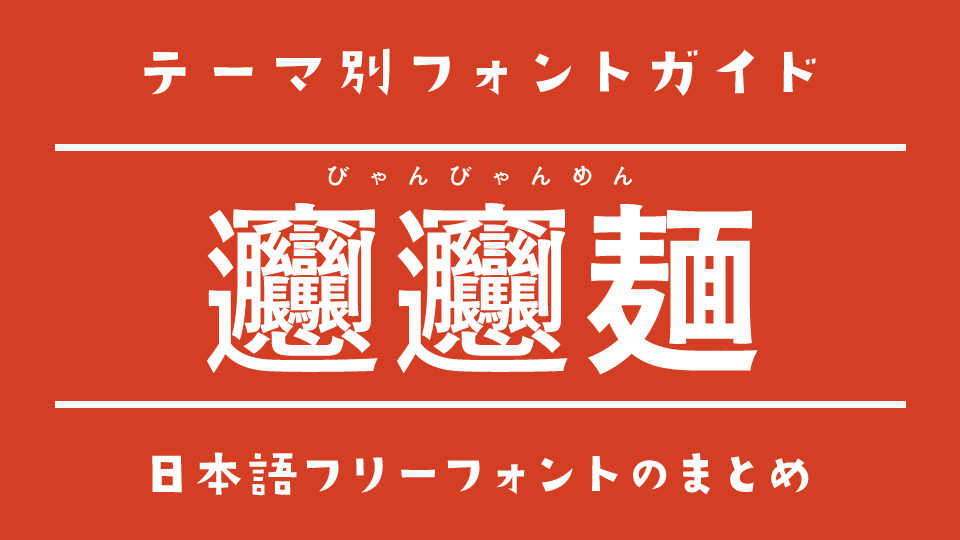
今回は、いざというときに役立つ「ビャンビャン麺」の文字を表示できる日本語フリーフォントをご紹介します。
「ビャンビャン麺」は、画数が非常に多く、一般的な日本語フォントでは表示できないこともある珍しい漢字です。入力したはずなのに四角い記号になったり、別のフォントへ自動的に置き換わったりして、デザイン制作で困った経験がある方もいるのではないでしょうか。
今回は、「ビャンビャン麺」という難しい表記に対応し、文字の形を正しく表示できるフリーフォントを厳選しました。中華料理店のメニューや旅行記事、難読漢字を扱うコンテンツ、フォントの収録文字を試したいときなど、いつか訪れるかもしれないを入力する日”に備えて、ぜひ参考にしてみてください。
「びゃん」が表示できる!びゃんびゃん麺対応の日本語フリーフォント
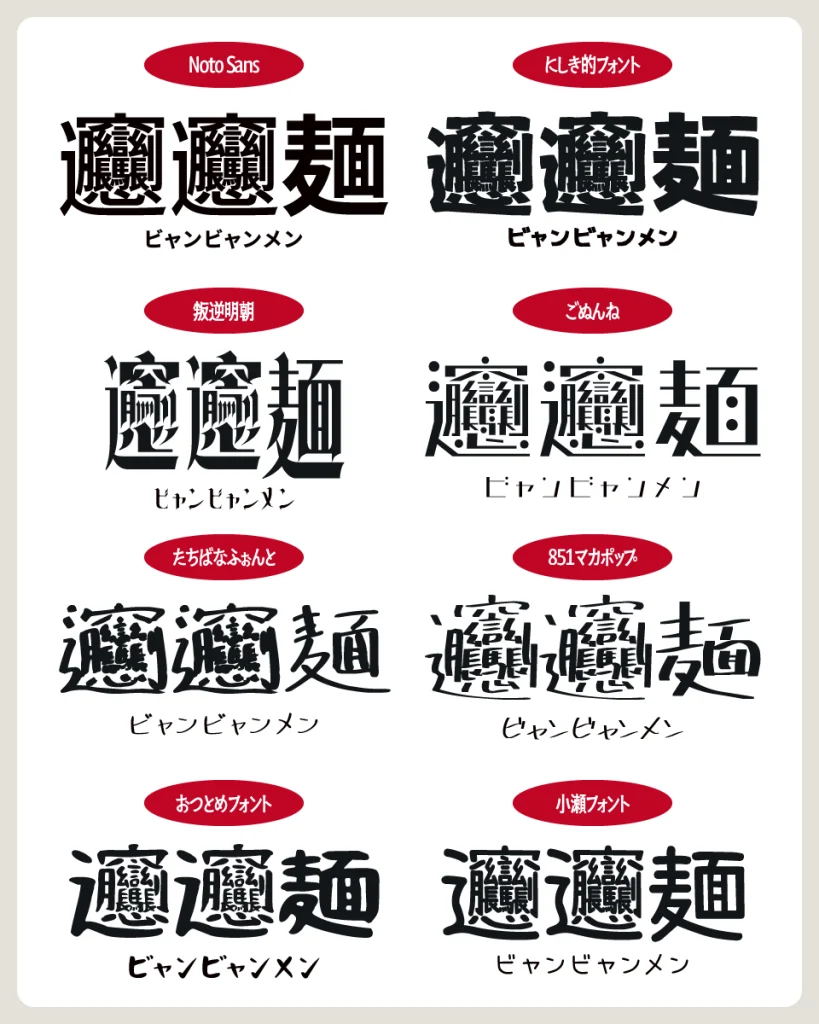
Noto Sans
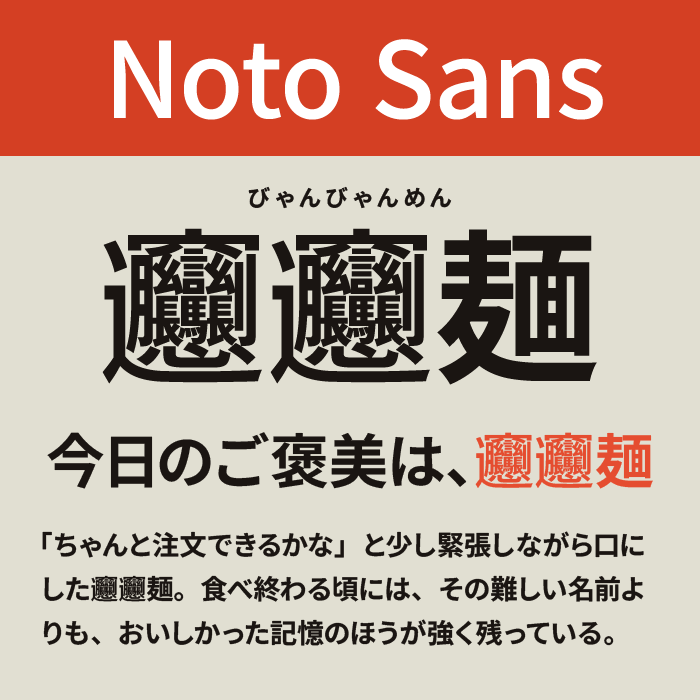
Noto Sansは、高い可読性と豊富な収録文字数を誇る定番のゴシック体フォントです。
世界中の文字を幅広くサポートしており、「ビャンビャン麺」のような非常に珍しい漢字も安心して表示できます。クセのないデザインなので、本文から見出しまで幅広く使える万能なフォントです。
Nishiki-teki(にしき的)
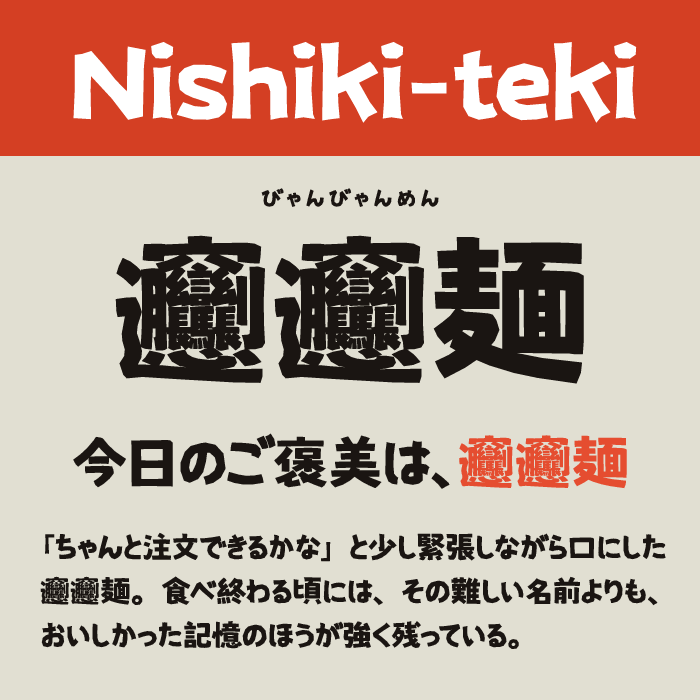
にしきてきは、太めでどっしりとした骨格を持ちながら、わずかにラフな手書きっぽさのある表情を感じられるフォントです。
力強い存在感があり、画数の多い「ビャンビャン麺」のような難しい漢字も潰れにくく、しっかりと読み取れます。見出しやタイトルに使うだけで印象がぐっと引き締まり、インパクトのあるデザインに仕上げられるフォントです。
たちばなふぉんと
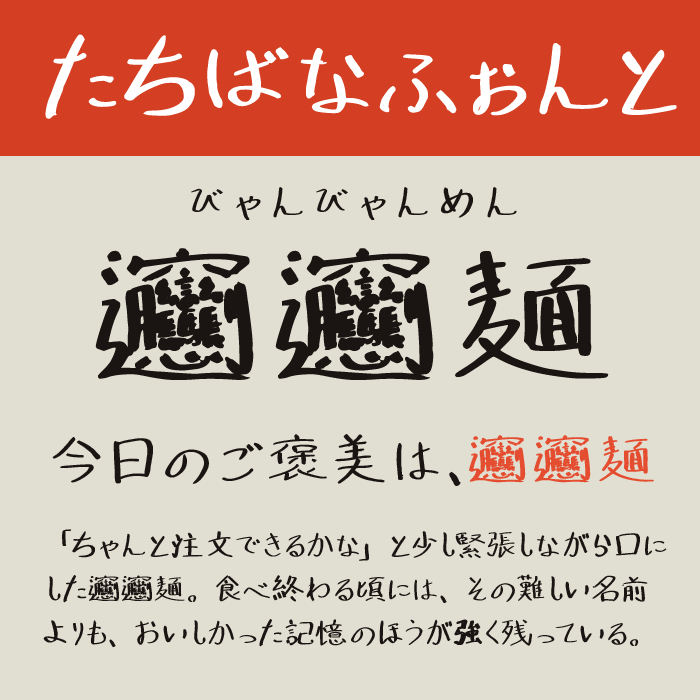
たちばなふぉんとは、俳優『立花裕大』さんによる手書きフォントです。
ゆるくて温かみのある柔らかな文字ながら、収録文字数が豊富で「ビャンビャン麺」のような珍しい漢字にも対応しています。肩の力を抜いた親しみやすいデザインを作りたいときに活躍するフォントです。
851マカポップ
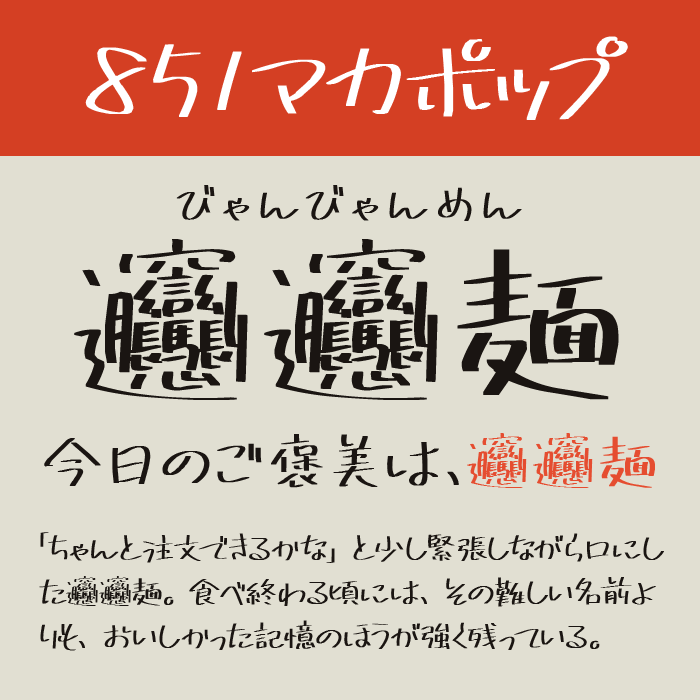
851マカポップは、マーカーペンで書いたような手書きの自由な線とポップな雰囲気が魅力のフォントです。
軽快で楽しい印象がありながら、画数の多い漢字もしっかり表示できます。「ビャンビャン麺」のような珍しい文字も可愛らしく見せられるため、親しみやすいデザインを作りたいときに活躍するフォントです。
おつとめフォント
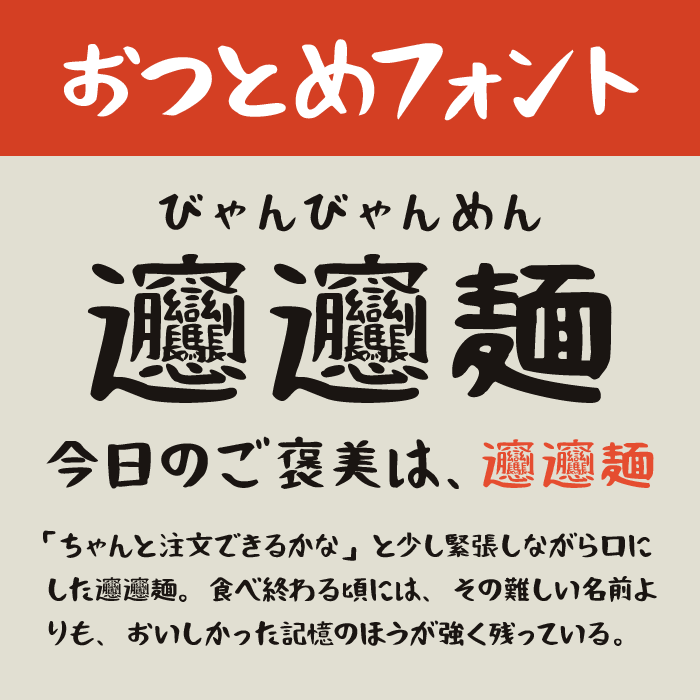
おつとめフォントは、丸みと力強さを兼ね備えた親しみやすい手書きフォントです。
やや太めの筆致が特徴で、難しい漢字でも視認性を保ちながら温かみを感じさせます。「ビャンビャン麺」のようなインパクトのある文字も、柔らかく親近感のある印象で表現できるフォントです。
小瀬フォント(瀬戸フォント)
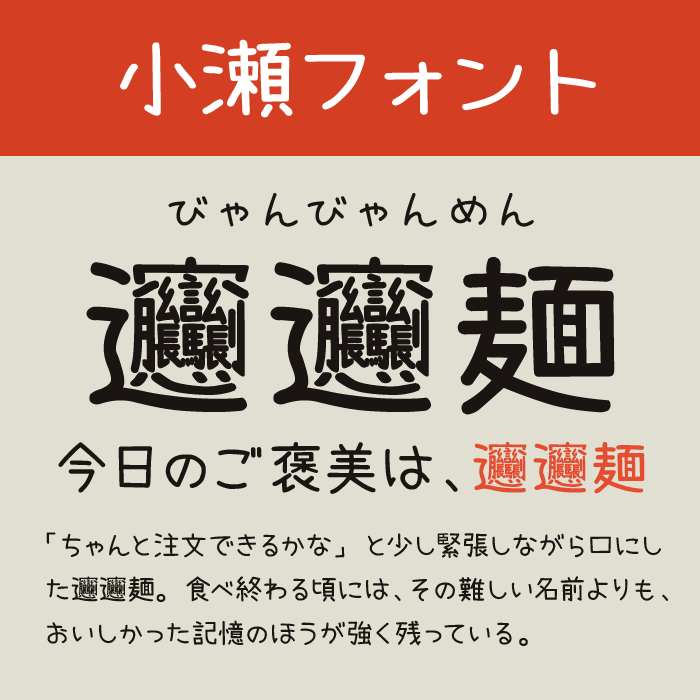
小瀬フォントは、やわらかな筆文字のような自然な表情を持つフォントです。
素朴で読みやすく、長文にも使いやすいデザインが特徴です。「ビャンビャン麺」のような特殊な漢字にも対応しており、温かみのある和風デザインや飲食店のメニューにもよく馴染みます。
Xim Sans
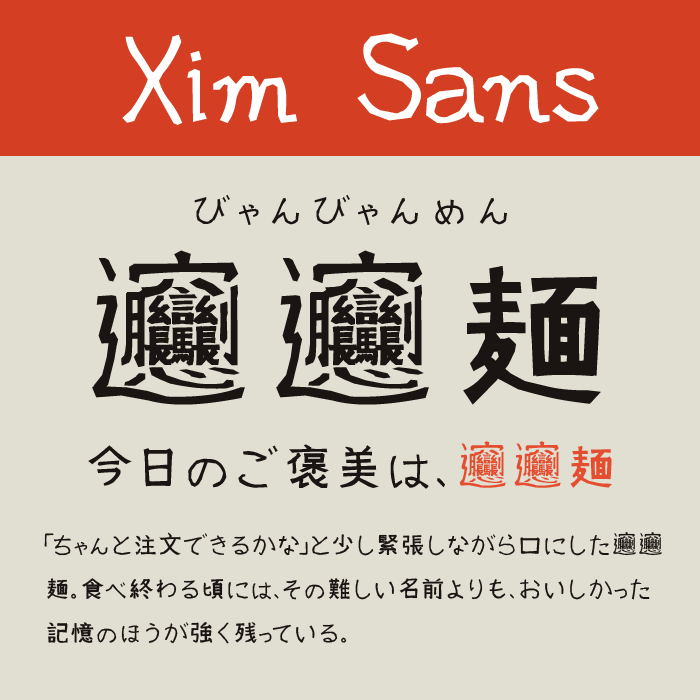
Xim Sansは、手作業で描いたような独特の揺らぎが魅力のサンセリフフォントです。
個性的でありながら可読性も高く、複雑な漢字も軽やかに表現できます。「ビャンビャン麺」のような難読漢字にも対応しており、遊び心のあるデザインにぴったりなフォントです。
京華老宋体
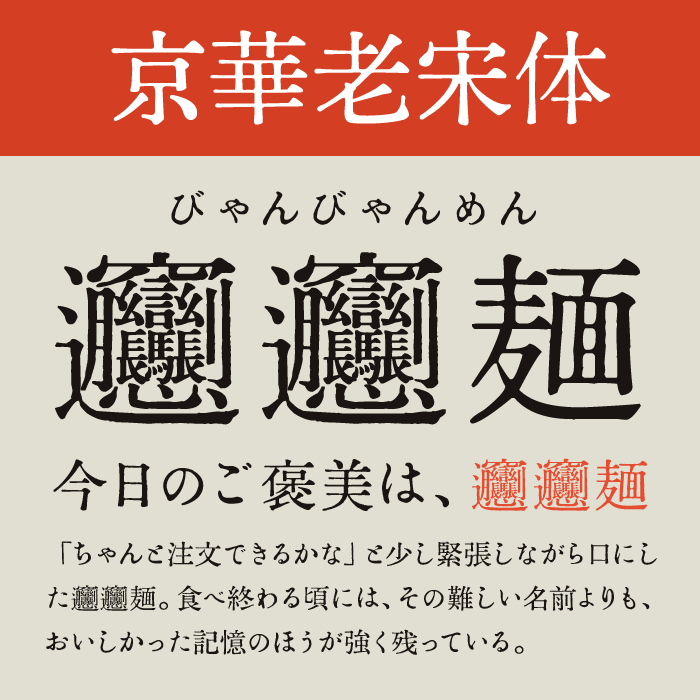
京華老宋体は、中国の宋体を思わせる優雅で端正なデザインが魅力のフォントです。
細身ながら凛とした存在感があり、中国語由来の「ビャンビャン麺」との相性も非常に良く、本場の雰囲気を感じさせるデザインに仕上がります。落ち着いた高級感を演出したい場面にもおすすめです。
築豊35ポイント
築豊35ポイントは、新聞や活版印刷を思わせる力強いオールド系のゴシック体フォントです。
どっしりとした太さと高い視認性が特徴で、複雑な漢字でも潰れにくく、読みやすさを保っています。「ビャンビャン麺」のような画数の多い文字も安定感のある印象で表現できるフォントです。
あいのてフォント
あいのてフォントは、相生創さんによる軽やかで風通しのよい手書きフォントです。
ラフで親しみやすい雰囲気がありながら、収録文字数が豊富で「ビャンビャン麺」のような珍しい漢字にも対応しています。日記やエッセイのような温かみを演出したい場面にぴったりなフォントです。
GLT-ごぬんね
ごぬんねは、極細の線で構成されたレトロな雰囲気が魅力のフォントです。ドット絵のようなシンプルな骨格を持ちながら、どこか懐かしいデジタル感もあり、珍しい漢字を表示しても雰囲気を損ないません。個性的でありながら読みやすく、「ビャンビャン麺」のようなインパクトのある文字もすっきり見せられるフォントです。
叛逆明朝
叛逆明朝は、鋭く伸びるウロコと力強い縦画が印象的な明朝体フォントです。クラシカルな美しさの中に反骨精神を感じさせるデザインで、難しい漢字でも堂々とした存在感を放ちます。「ビャンビャン麺」のような複雑な文字も品よく表現でき、和風作品や文学的なデザインとの相性も抜群です。
源泉丸ゴシック
源泉丸ゴシックは、丸みのあるやさしいフォルムと、しっかりした太さを兼ね備えたゴシック体フォントです。親しみやすさがありながら画数の多い漢字も美しく表示でき、「ビャンビャン麺」のような難しい文字も読みやすく仕上がります。幅広い用途で安心して使える定番フォントです。